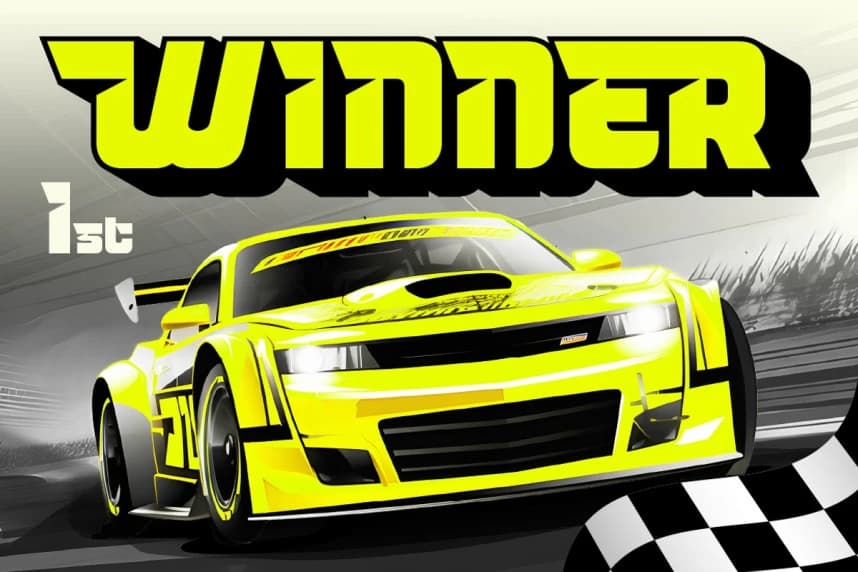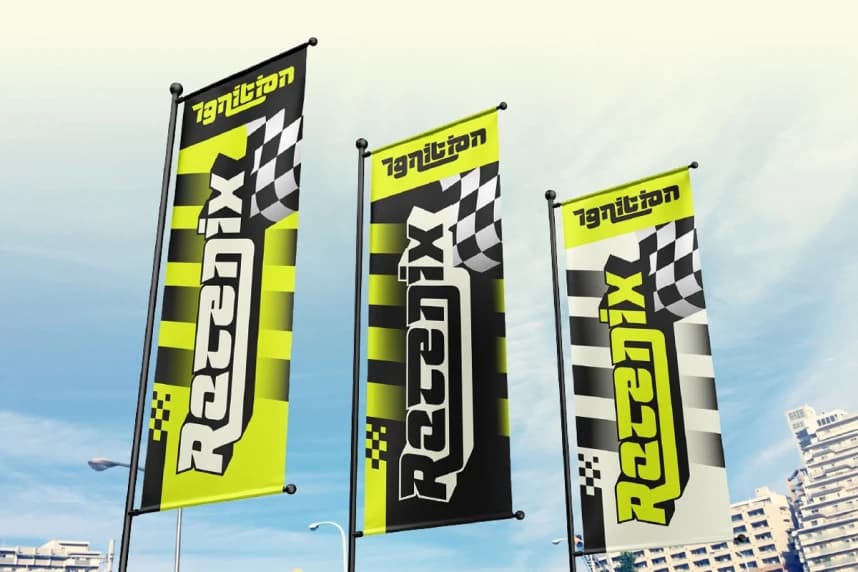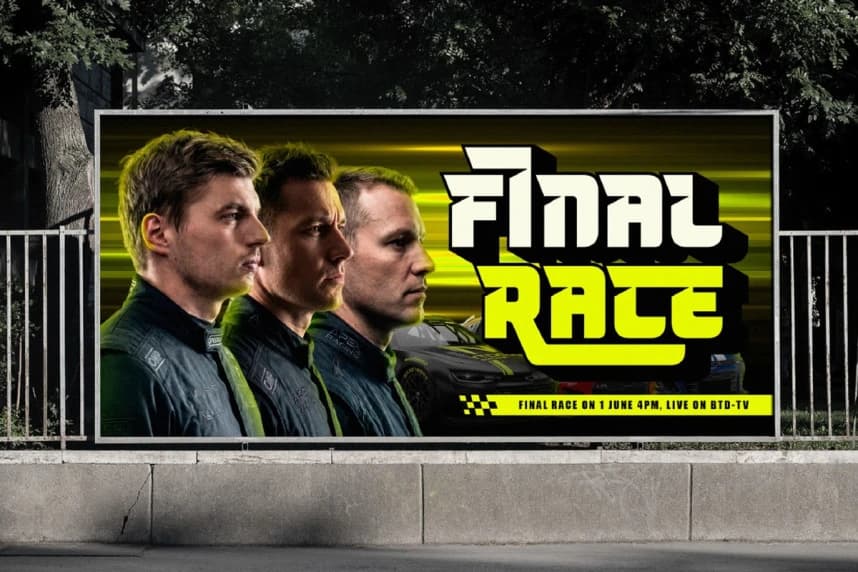
Trivox Font
Trivox Font o enerjiden doğdu, tasarımlarınıza hız, güç ve geleceğe yönelik bir hava katmak için tasarlanmış cesur ve agresif bir modern spor fontudur. Yarış kültüründen, motor sporları grafikleri ve yüksek performanslı markalaşmadan ilham almıştır.
Trivox Font, o enerjiden doğmuştur; tasarımlarınıza hız, güç ve gelecekçi bir atmosfer katmak üzere tasarlanmış cesur ve agresif bir modern spor fontudur. Yarış kültüründen, motorsporları grafikleri ve yüksek performanslı markalaşmadan ilham almıştır.